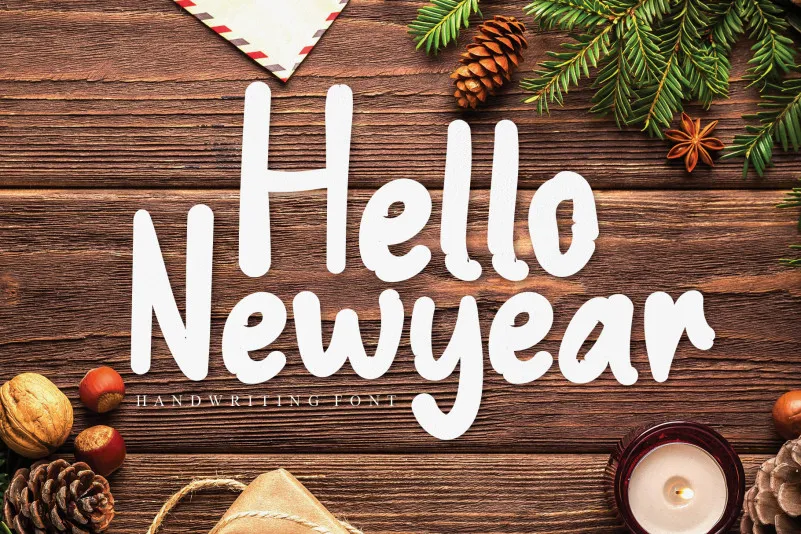
Hello New Year Display Font – Fonte Grátis
Hello New Year Display Font
A fonte “Hello New Year Display Font” é uma escolha perfeita para criar mensagens impactantes no período de inverno e comemorações importantes do ano. Suas letras redondas e robustas têm um toque moderno que traz alegria às suas criações, tornando-as ainda mais destaque em qualquer projeto gráfico. Para quem busca uma fonte com cara de festa para celebrar o início de um novo ano, esta é uma ótima opção. Suas linhas grossas e desenhos arredondados destacam-se perfeitamente nas aplicações digitais, impressas ou em telas tácteis. Este font se adequa às ocasiões de verão como o natal, ano novo, Carnaval e Festa Junina. Ele adicionará um toque divertido e moderno a qualquer design que ele seja aplicado, tornando-o mais chamativo e envolvente para seus destinatários. Com “Hello New Year Display Font”, você poderá criar mensagens de boas-vindas ao novo ano que destacam-se das demais. É uma ótima maneira de começar o ano com estilo, criatividade e bom humor.